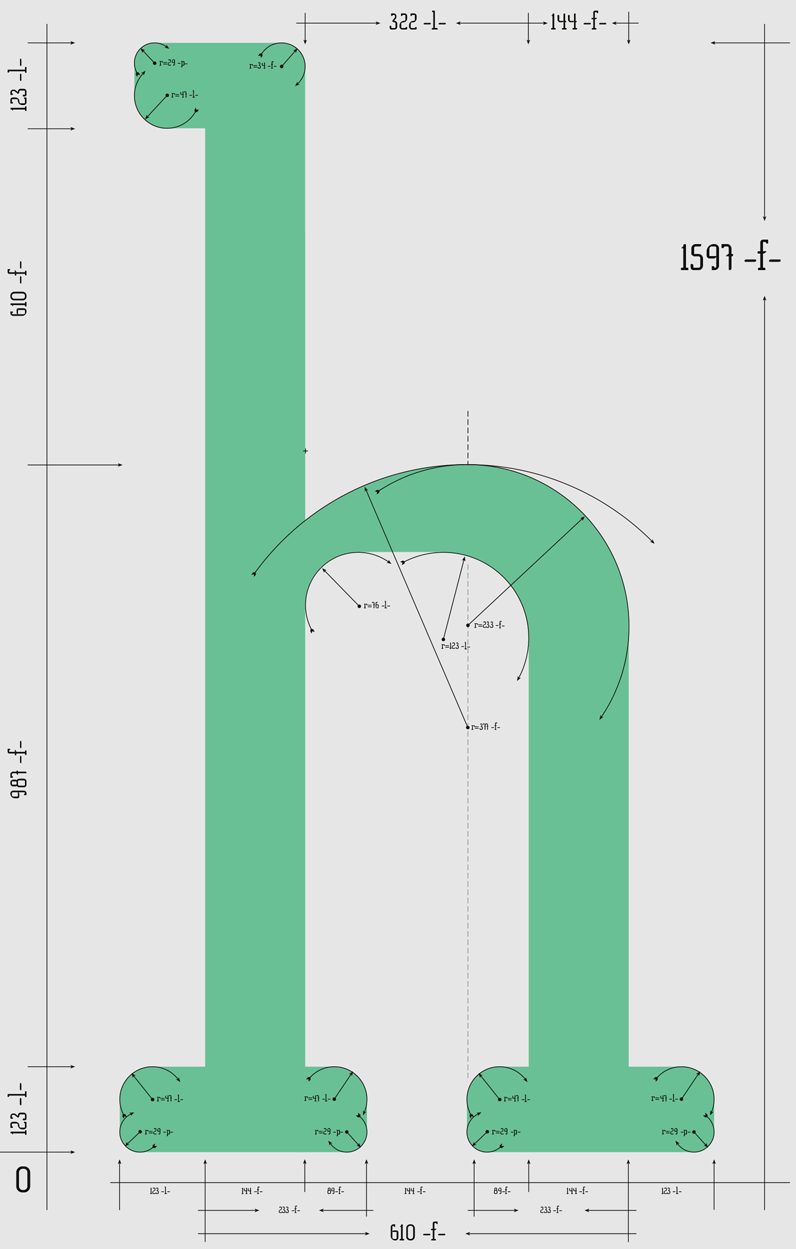
Esta es una fuente semi condensada con Slab Serif y corresponde a mi serie de tipografías construidas con proporciones derivadas de secuencias matemáticas. Un experimento en el sentido de las proporciones, para definir todas ellas me he basado principalmente en la secuencia de Fibonacci, también he usado algunos números de la secuencia de Lucas y para las hendiduras en los nudos de las astas y algunos signos de puntuación he usado el triángulo de Kepler. Todo el kerning y espaciado de la fuente está definido completamente con cifras de las secuencias de Fibonacci y Lucas.
El uso práctico de esta fórmula se puede ver en el póster constructivo de la letra ‘h’ minúscula, observar las proporciones que inscriben la letra, 1597×610 pt, dos números correlativos de la sucesión de Fibonacci que conforman lo que se conoce como rectángulo áureo.Toda la definición de espacio entre caracteres y kerning así como como el espaciado de palabras (Tracking) está definido con números de las siguientes secuencias matemáticas.
Fibonacci: 0, 1, 2, 3, 5, 8, 13, 21, 34, 55, 89, 144, 233, 377, 610, 987, 1597…
Lucas: 2, 1, 3, 4, 7, 11, 18, 29, 47, 76, 123, 199, 322, 521, 843, 1364, 2207…
Tribonacci: 1, 2, 4, 7, 13, 24, 44, 81, 149, 274, 504, 927, 1705, 3136…
Fuente Fibonacci
Estilo: Slab Serif
Proporción: Regular, Condensada
Glyphs: 476
Funciones OpenType: Additional languages, Capital Spacing, Contextual Alternates, Denominators, Discretionary Ligatures, Extended Fractions, Historical Ligatures, Inferiors, Kerning, Mathematical Greek, Numbers Small Caps, Numerators, Ordinals, Scientific Inferiors, Slashed Zero, Standard Ligatures, Subscript, Titling alternates.